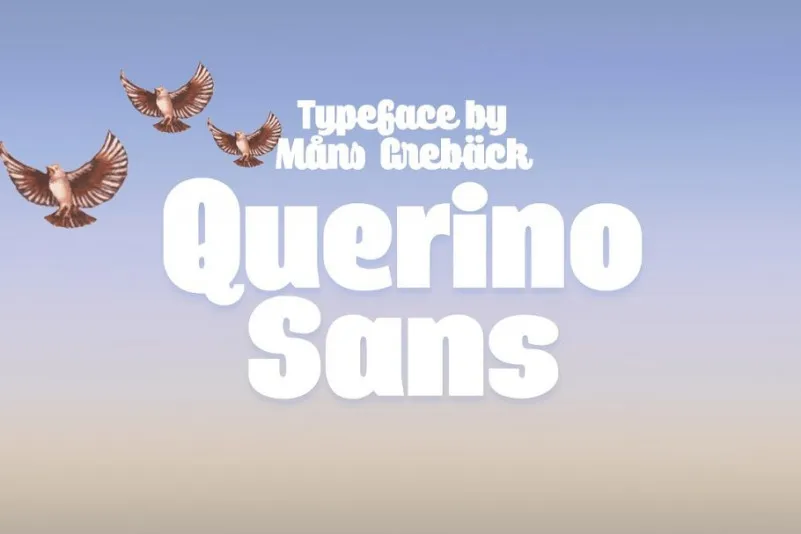
A Befonts está entusiasmada em apresentar uma nova fonte sans-serif chamada Querino Sans Serif. Esta fonte é inspirada nos tipos de letra sans serif modernos e elegantes que são populares nas edições de alta qualidade do design editorial. Ela se destaca perfeitamente para uso em designs de títulos, tornando-a uma excelente opção para um amplo range de usos, incluindo apresentações, revistas, placas, logotipos e mais. Querino Sans Serif é uma fonte extra-bold desenvolvida por Måns Grebäck durante 2018 e 2019. Ela chega tanto em versão regular e direita quanto em itálica. Para aqueles que querem experimentar algo diferente, também vale a pena explorar sua irmã tipoface, Querino Script. Este conjunto de fontes pode ser perfeito para uso em variados ambientes empresariais, como apresentações, revistas, placas, logotipos e outros materiais relacionados ao negócio. Além disso, o estilo distinto da Querino Sans Serif pode transformar qualquer documento ou projeto em algo chamativo e profissional.